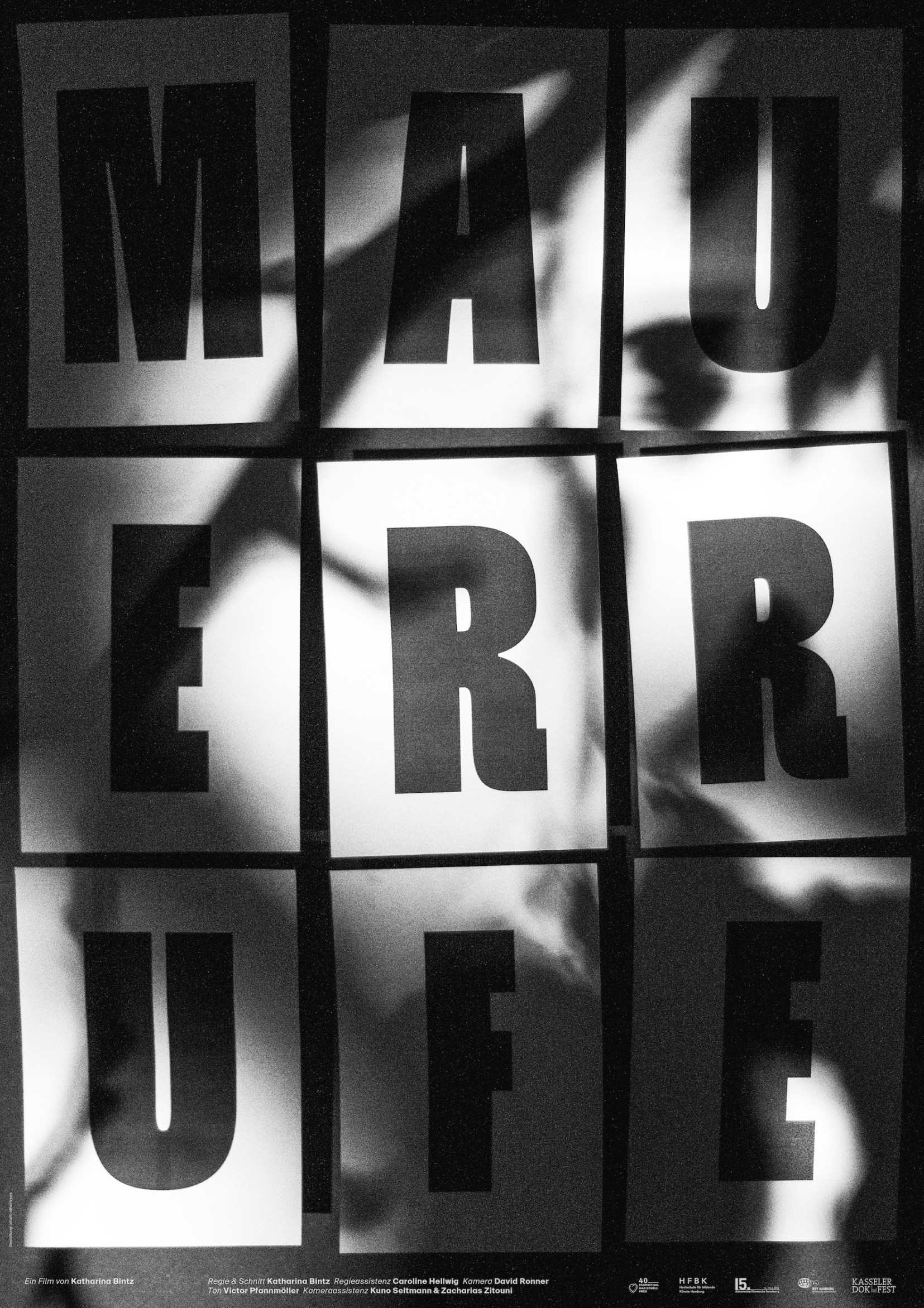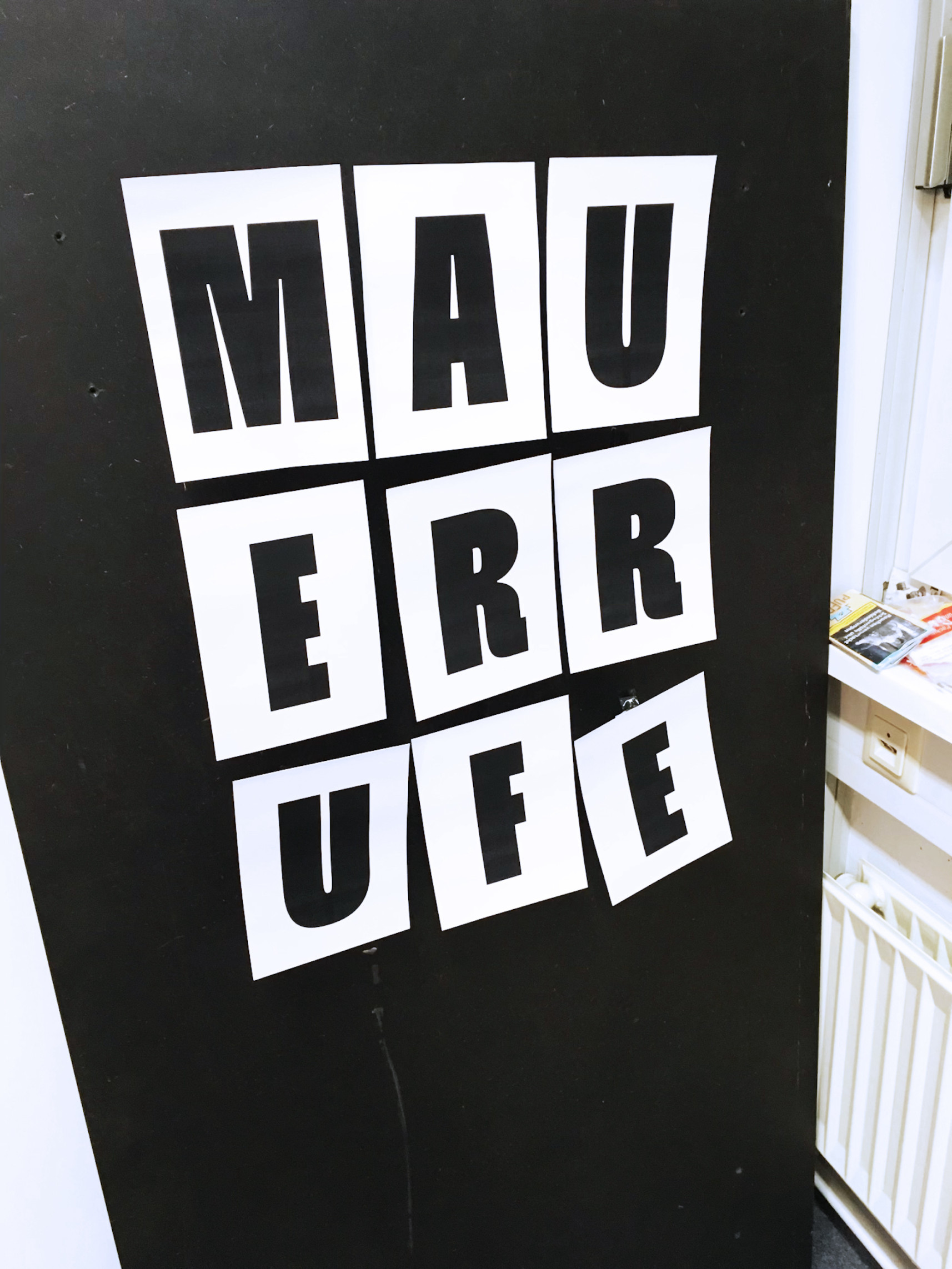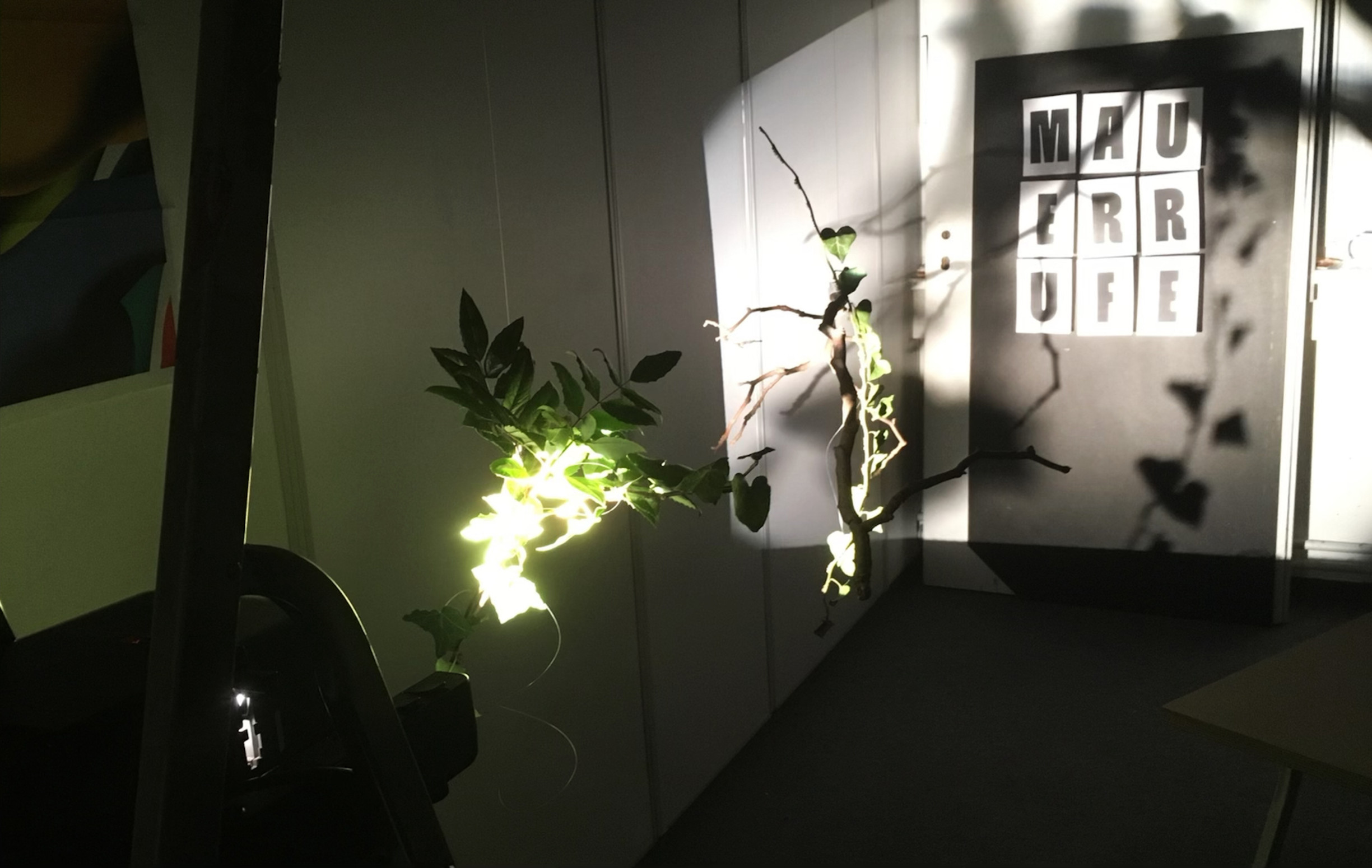
Mauerrufe
Film, Plakat
Der Film Mauerrufe von Katharina Binz handelt von dem Versuch der Angehörigen von Insassen der Untersuchungunshaftanstalt in Hamburg mit ihren Liebsten zu kommunizieren. Dabei sind es häufig Frauen, die im Park Planten un Blomen an der Mauer stehen und zu ihren Männern in den Fenstern rufen. Der Titel steht bei diesem Filmplakat im Vordergrund. Es entsteht ein Gitter durch die Anordnung der Buchstaben. Durch einen analogen Prozess mithilfe eines Dia-Projektors werden Schatten von Ästen und Blättern auf die Buchstaben geworfen. Das starke Rauschen des schwarz-weiß Films wird ebenso in die Gestaltung mit aufgenommen.
Schrift: Norbert von Philipp Neumeyer
& Suisse Intl. von Swiss Typefaces